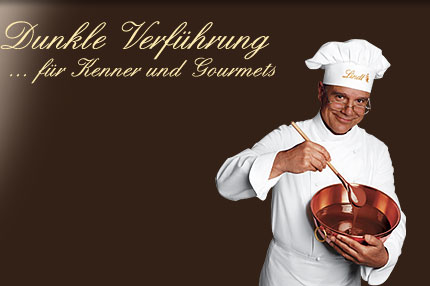
Lindt - Hausschrift
Welche Font kommt möglichst nah an die Lindt Hausschrift (Schreibschrift) ran?
Excelsior
Lettergieterij Amsterdam
Recht ähnlich:
Künstlerschreibschrift, D.Stempel
Lithographia
Aber beide haben mehr Schwünge.
Georg, das stimmt nicht. Das ist nicht die Excelsior.
Ja, Lars,
das weiß ich. Ich habe nur die Frage beantwortet:
"Welche Font kommt möglichst nah an die Lindt Hausschrift (Schreibschrift) ran?"
Und das ist wohl noch am ehesten die Excelsior.